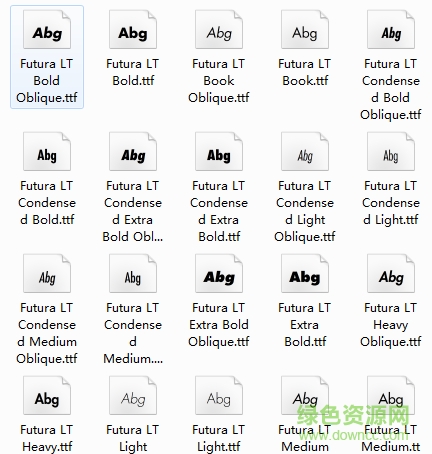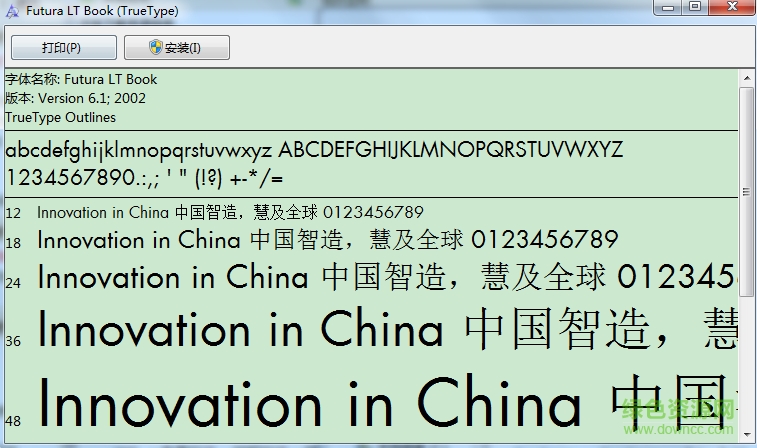
futura系列字體下載是一共20款全套英文標(biāo)準(zhǔn)設(shè)計(jì)字體,這些字體字體造型規(guī)整,筆畫勻稱,每款字體都有獨(dú)具特色的特點(diǎn),這些字體常用于產(chǎn)品設(shè)計(jì)、藝術(shù)設(shè)計(jì)等方面,有需要的朋友歡迎來綠色資源網(wǎng)下載使用。